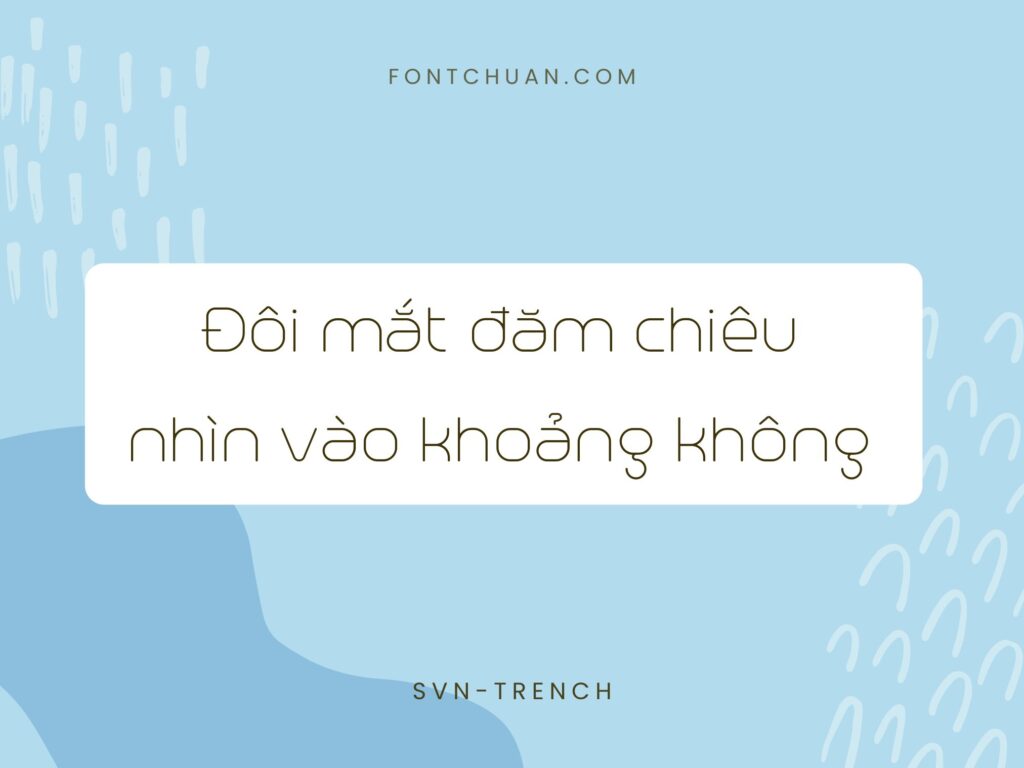
Font SVN Trench là phiên bản Việt hóa của kiểu chữ Trench, được thực hiện bởi STYLEno.1 Fonts. Trench là một kiểu chữ sans-serif hiện đại, được thiết kế bởi NimaVisual. Font này nổi bật với các đường nét đơn giản, gọn gàng và dễ đọc, phù hợp cho nhiều mục đích sử dụng khác nhau như thiết kế đồ họa, in ấn và web.
SVN Trench lý tưởng cho các dự án thiết kế yêu cầu sự rõ ràng và chuyên nghiệp, như thiết kế logo, tiêu đề, bao bì sản phẩm và các ấn phẩm quảng cáo. Các ngành nghề như quảng cáo, công nghệ và giáo dục có thể tận dụng font này để tạo điểm nhấn trong thiết kế. Ngoài ra, font cũng phù hợp cho các sự kiện như Tết, Giáng sinh, Valentine và các lễ hội khác.